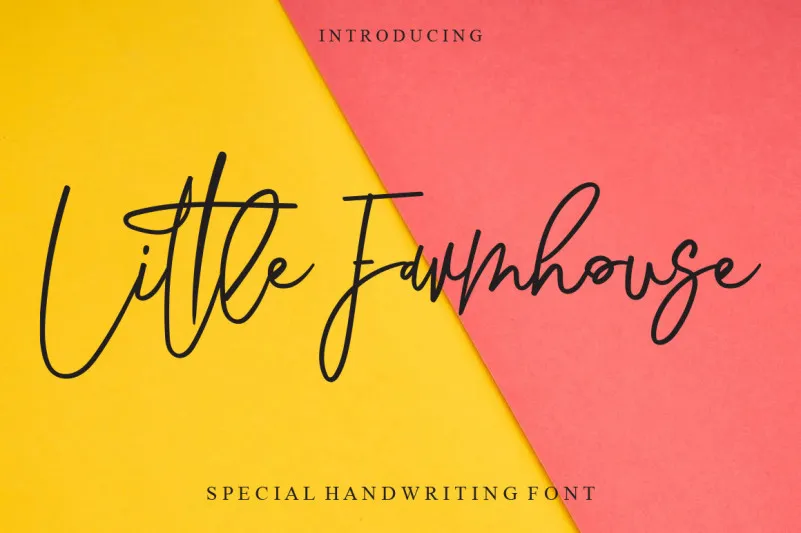
Little Farmhouse Font – Download Grátis
Esta é uma fonte escrita a mão delicada e autêntica. Desenvolvida com mestria para manter seu aspecto original e natural, essa font irá destacar suas criações e impactar seus espectadores. Ideal para adicionar um toque de personalidade única ao seu design, ela é uma escolha perfeita para quem busca expressar sua visão pessoal através de grafismo. Seja você designer gráfico, artista digital ou criador de conteúdo, essa fonte escrita a mão certamente complementará suas ideias e tornará seus projetos ainda mais impressionantes.